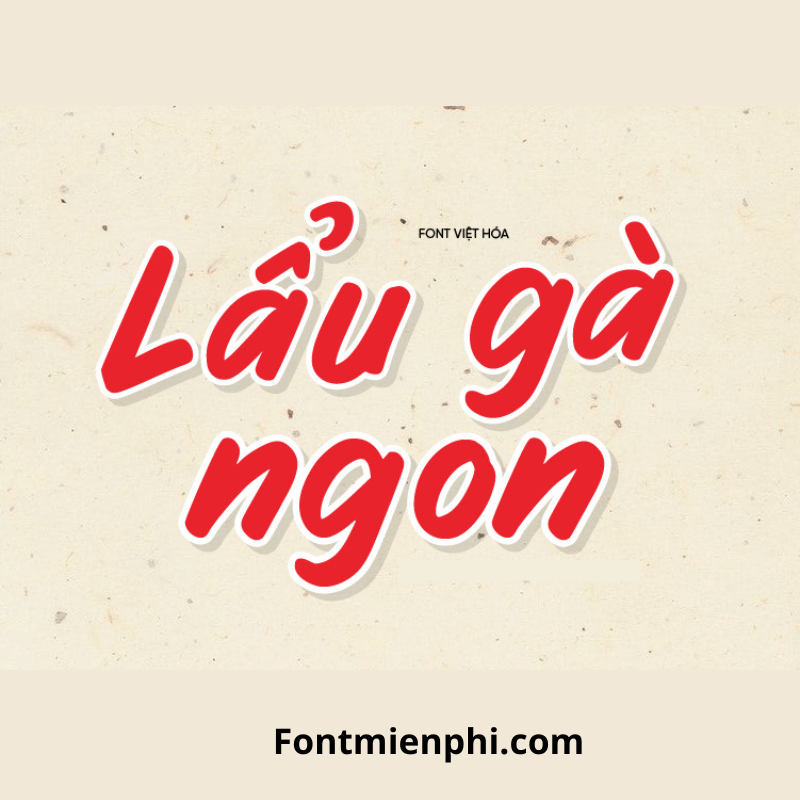
Font Việt hóa 1FTV VIP Fruity Stories
Font Việt Hóa 1FTV VIP Fruity Stories – Nét Chữ Độc Đáo, Sáng Tạo
Font Việt hóa 1FTV VIP Fruity Stories là bộ font chữ nghệ thuật độc đáo, được thiết kế dành riêng cho cộng đồng sáng tạo Việt. Với phong cách vui tươi, bắt mắt, font chữ này phù hợp cho thiết kế poster, bìa sách, truyện tranh và các dự án nghệ thuật khác.
• Thiết kế sinh động: Lấy cảm hứng từ phong cách hoạt hình, Fruity Stories mang đến nét chữ mềm mại, đầy màu sắc, giúp sản phẩm thiết kế trở nên thu hút.
• Hỗ trợ tiếng Việt: Font được Việt hóa chuẩn, đảm bảo hiển thị rõ ràng các ký tự có dấu, phù hợp với mọi nhu cầu sử dụng.
• Đa dạng ứng dụng: Dùng cho in ấn, digital art, social media, hoặc các ấn phẩm quảng cáo.
1FTV VIP Fruity Stories là lựa chọn tuyệt vời cho những ai yêu thích phong cách font chữ nghệ thuật, trẻ trung. Tải ngay để khám phá những ý tưởng thiết kế độc đáo và ấn tượng!